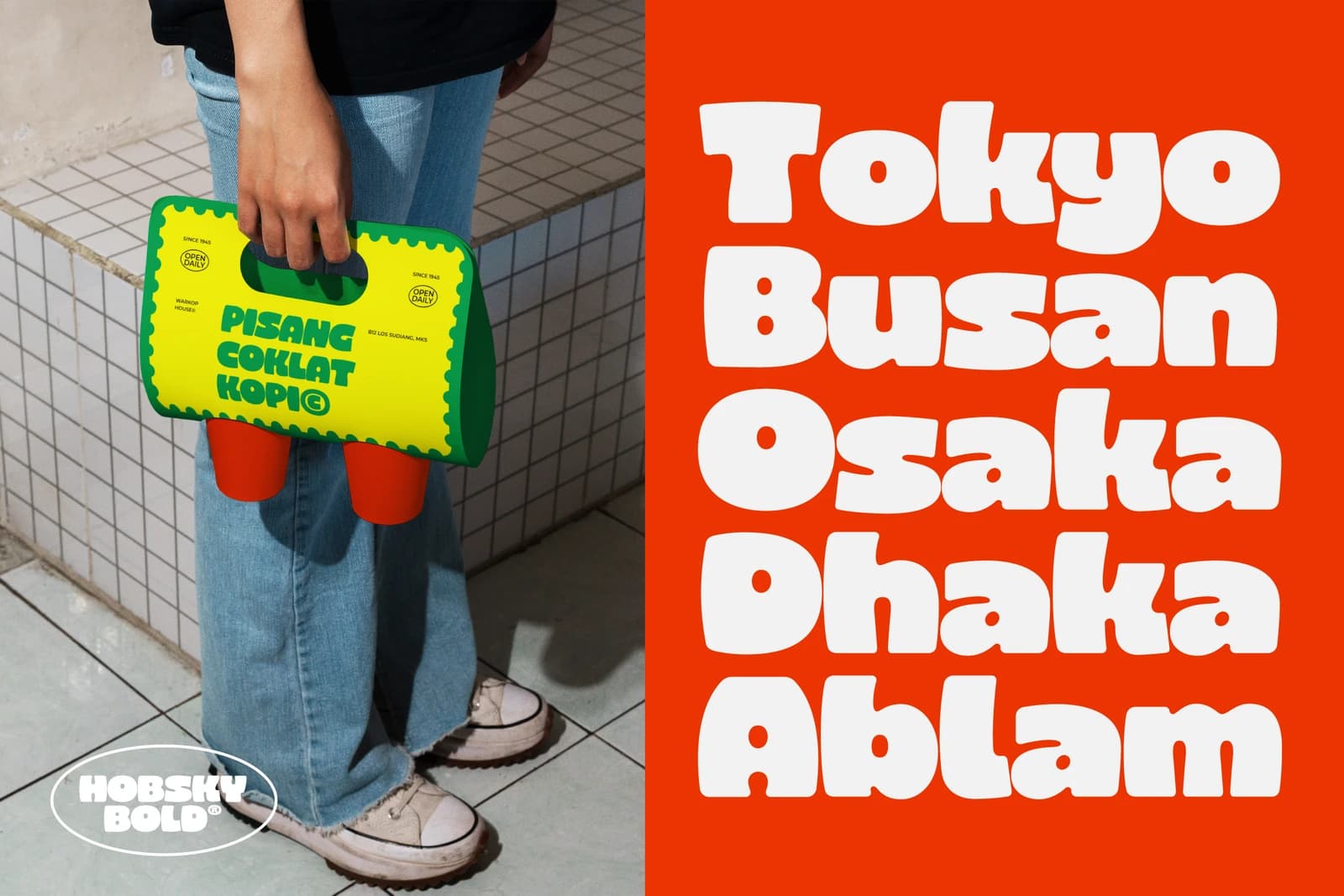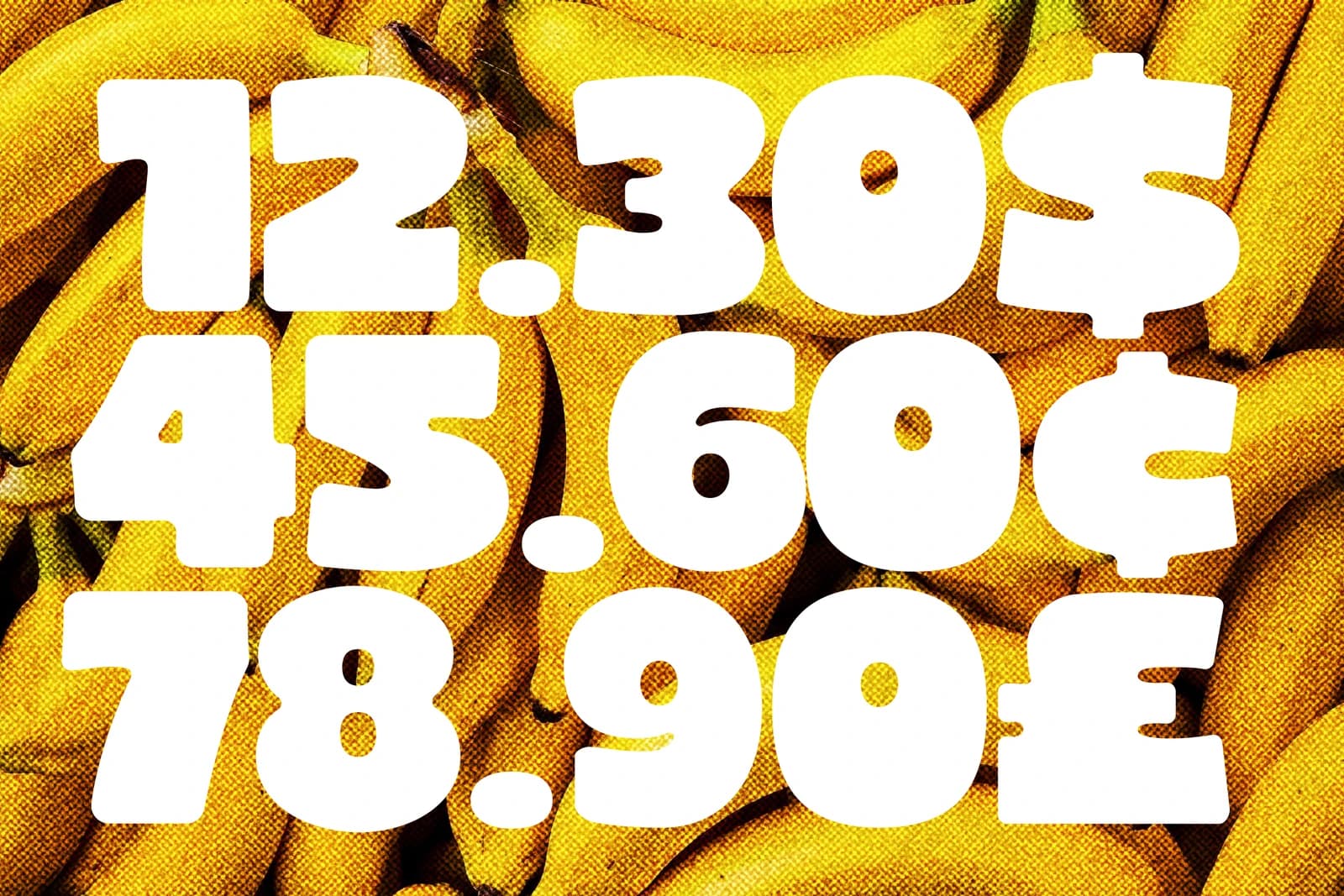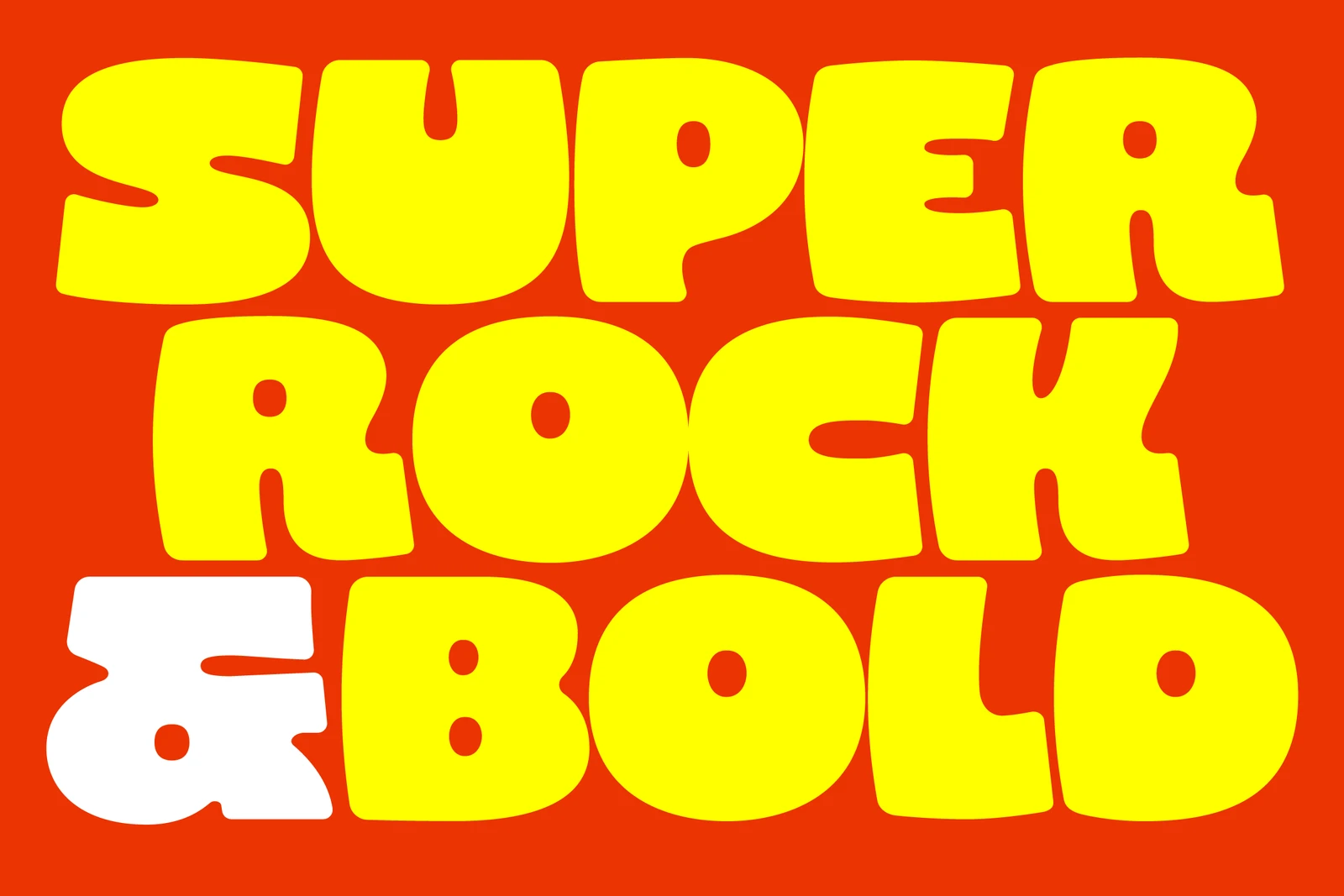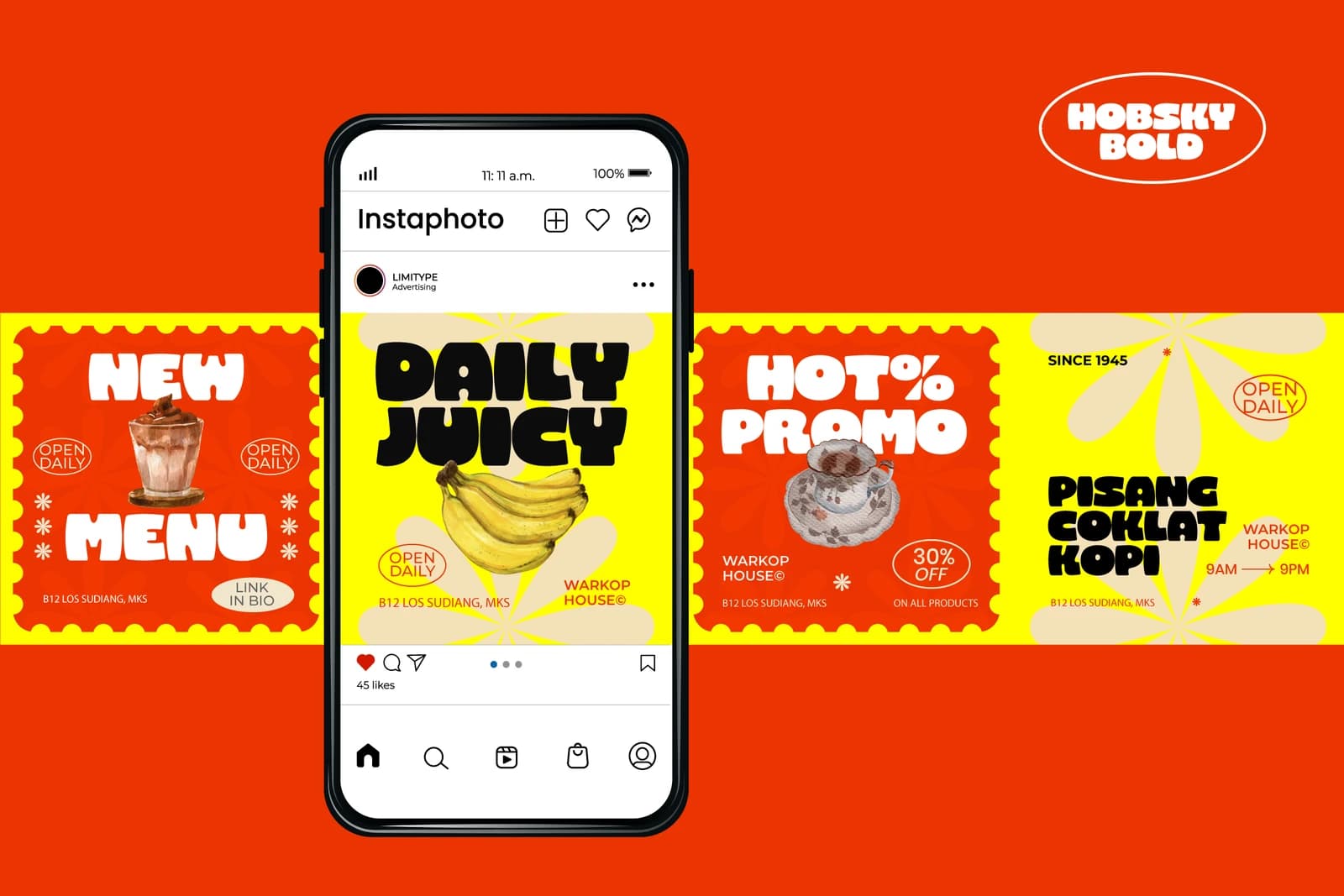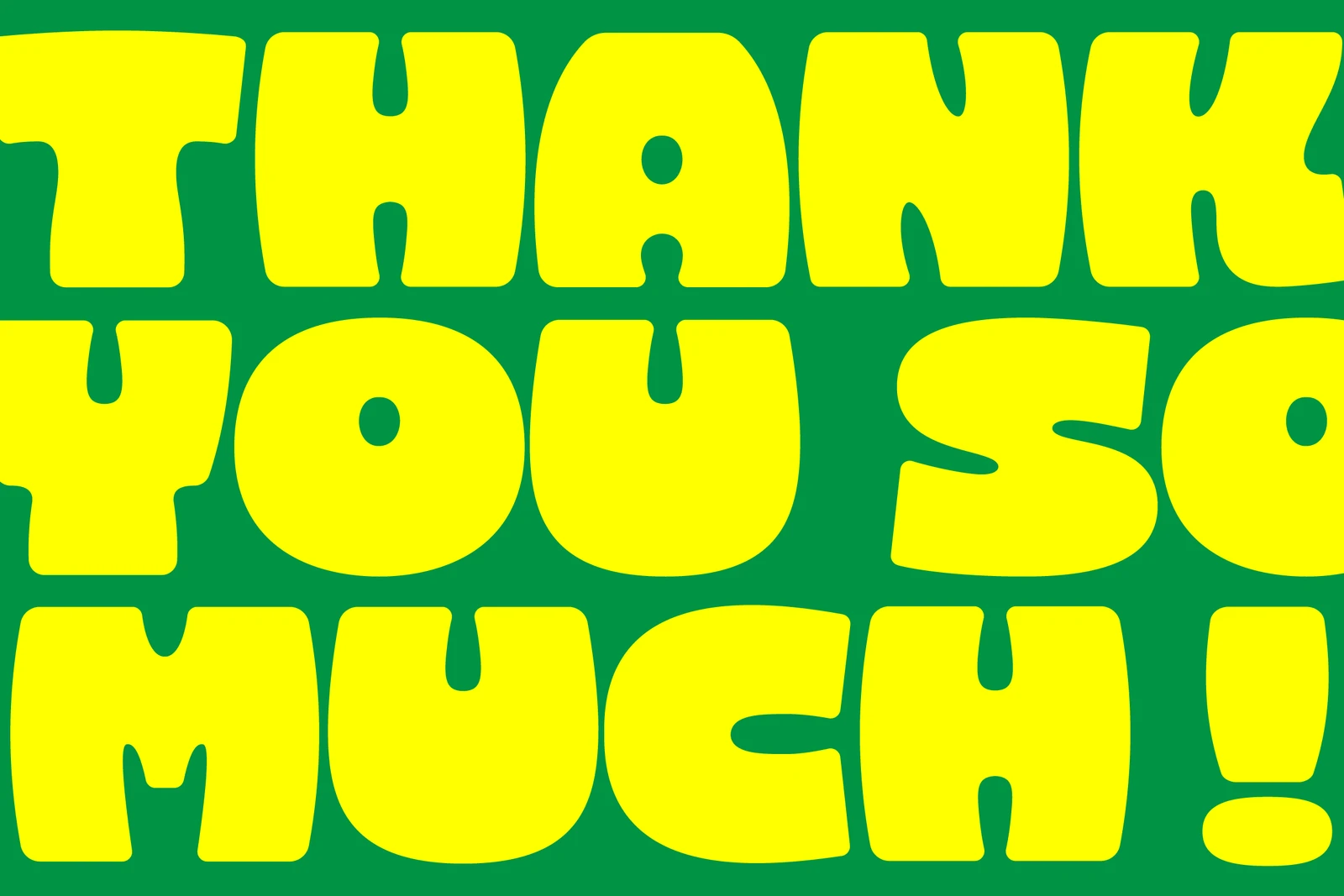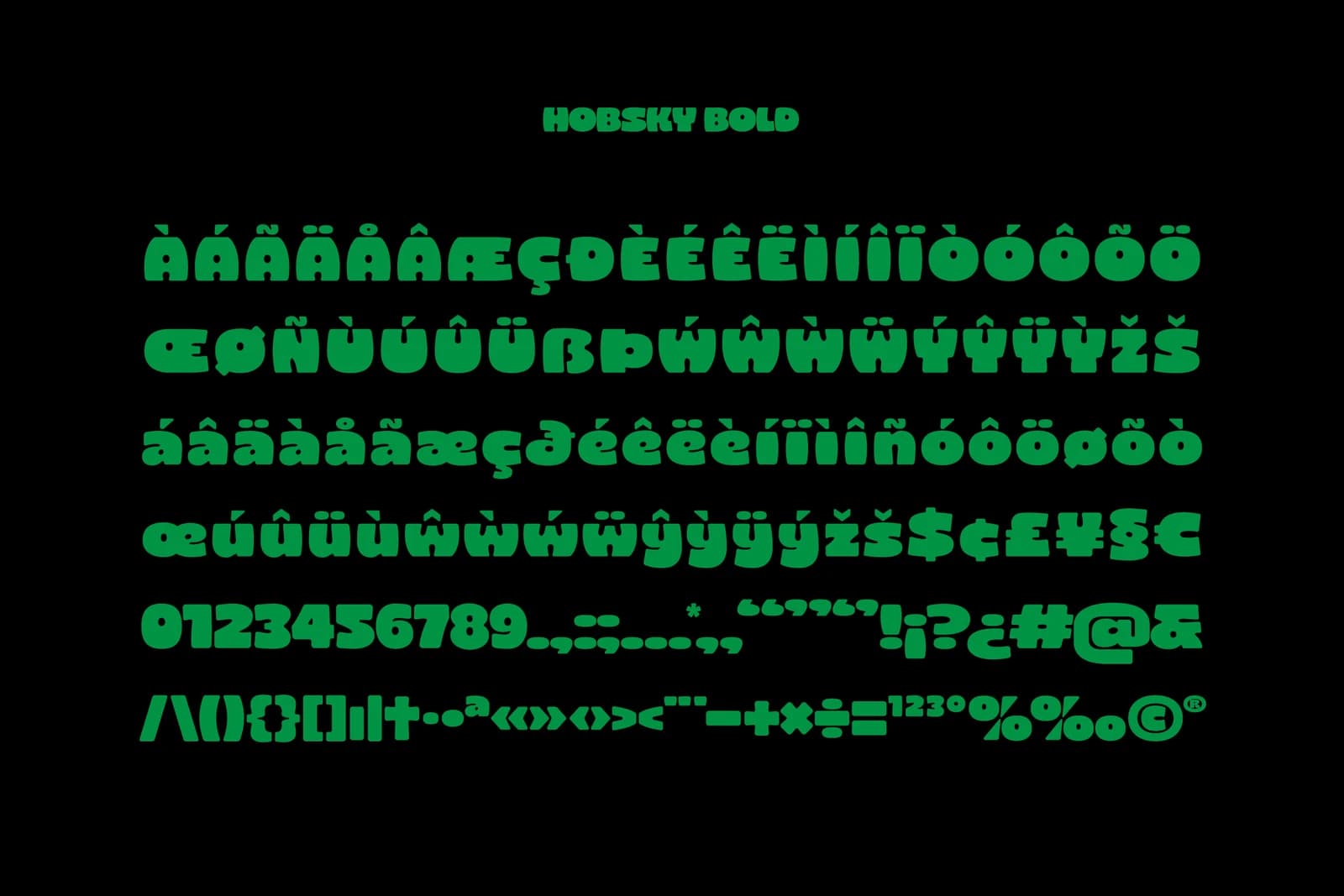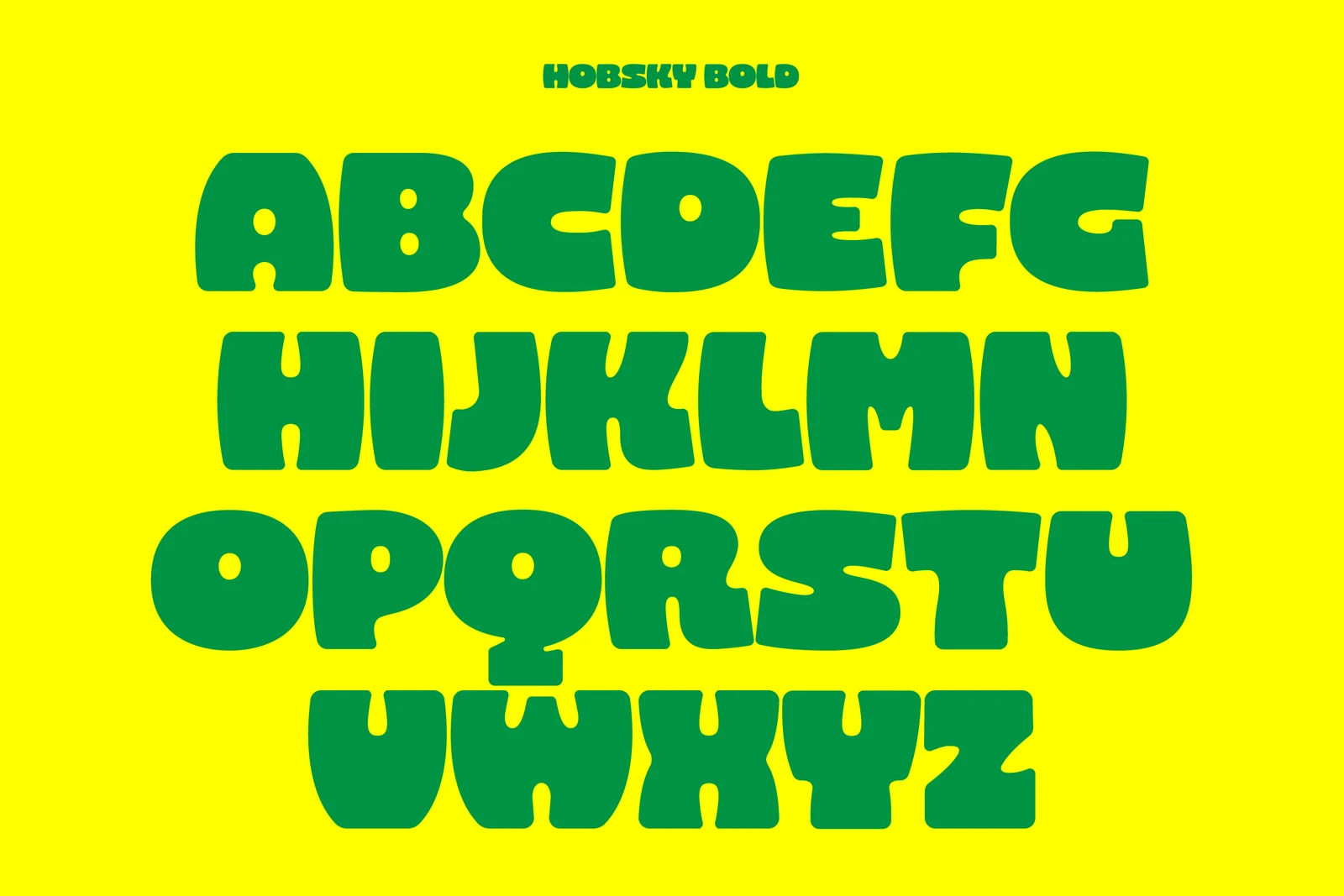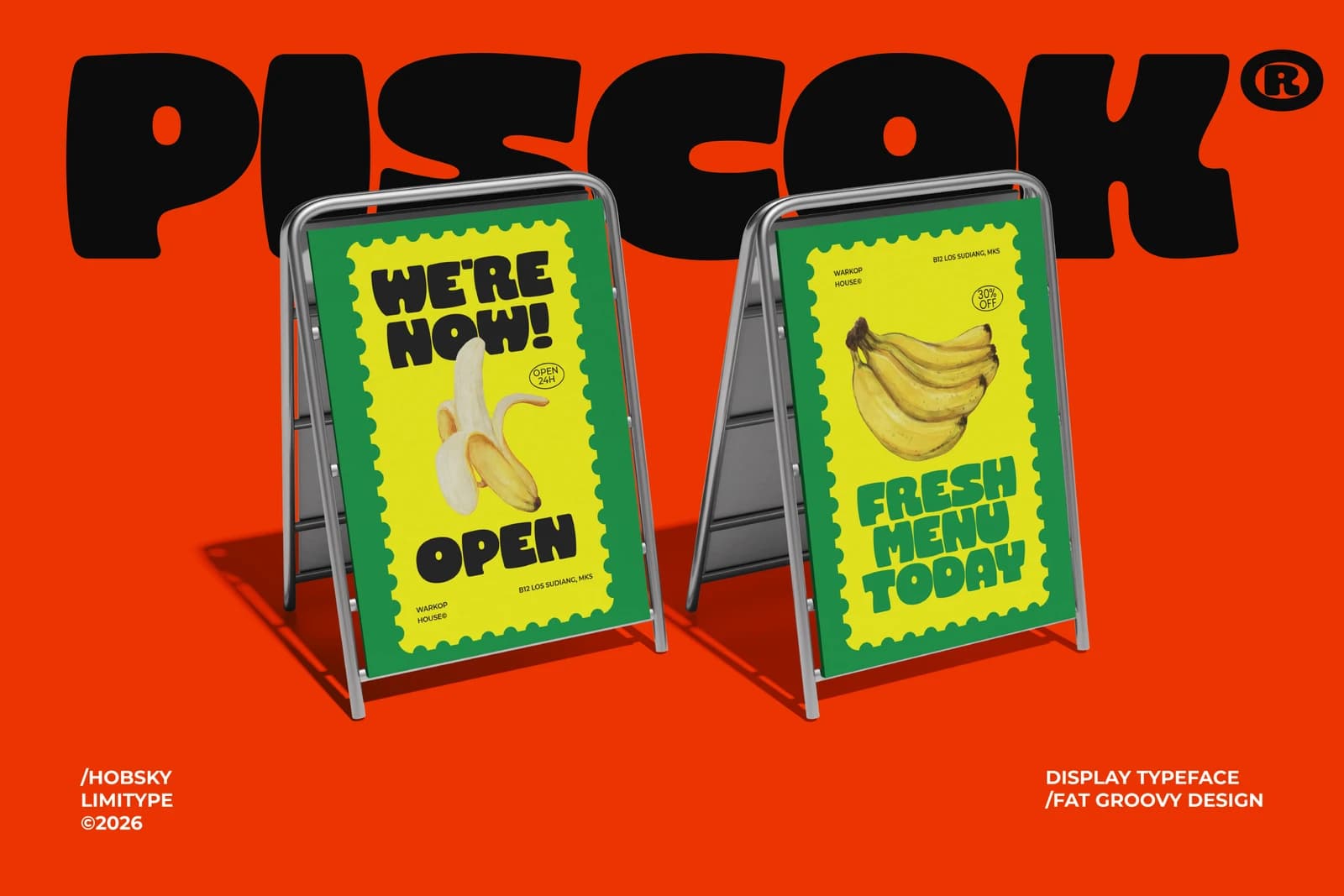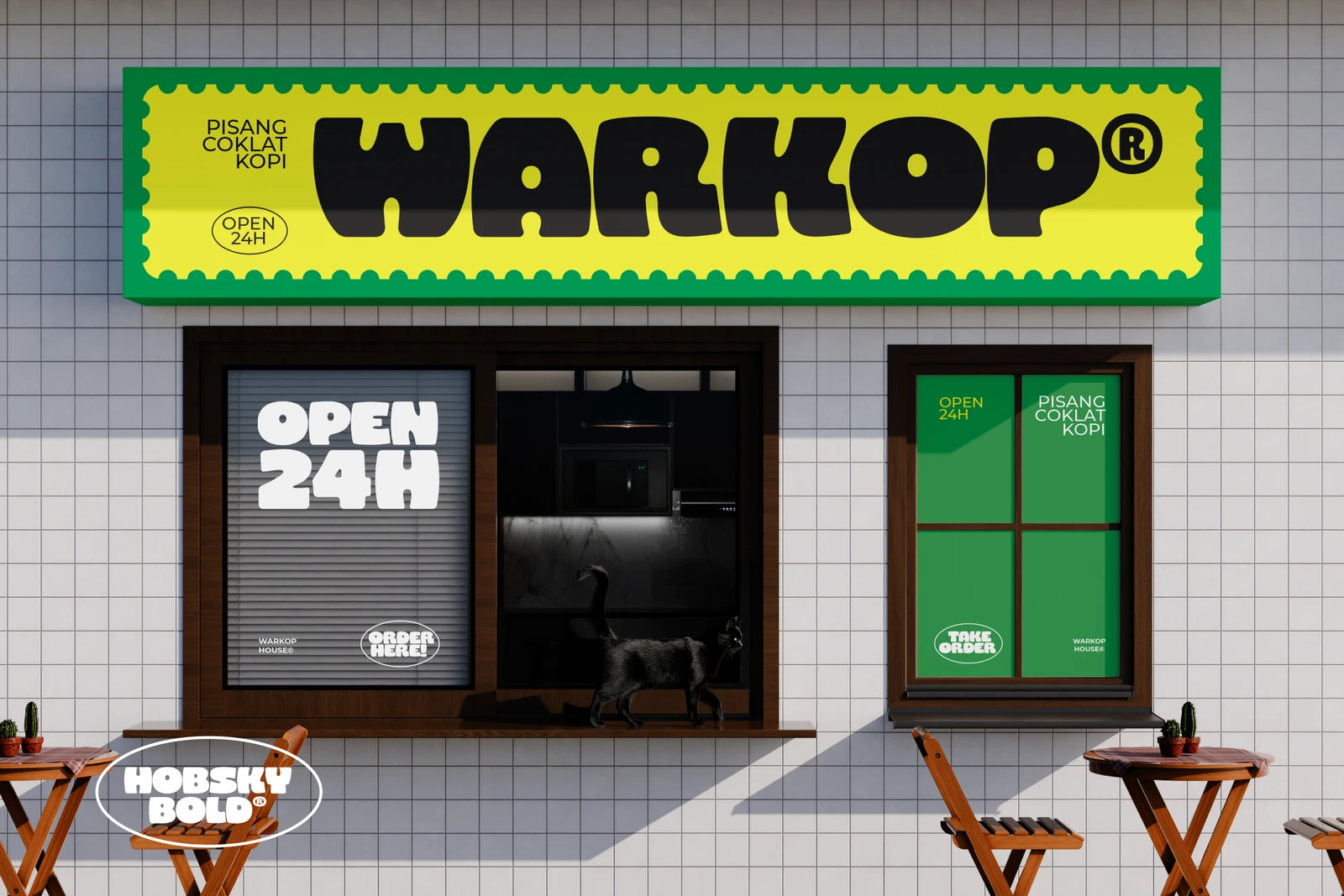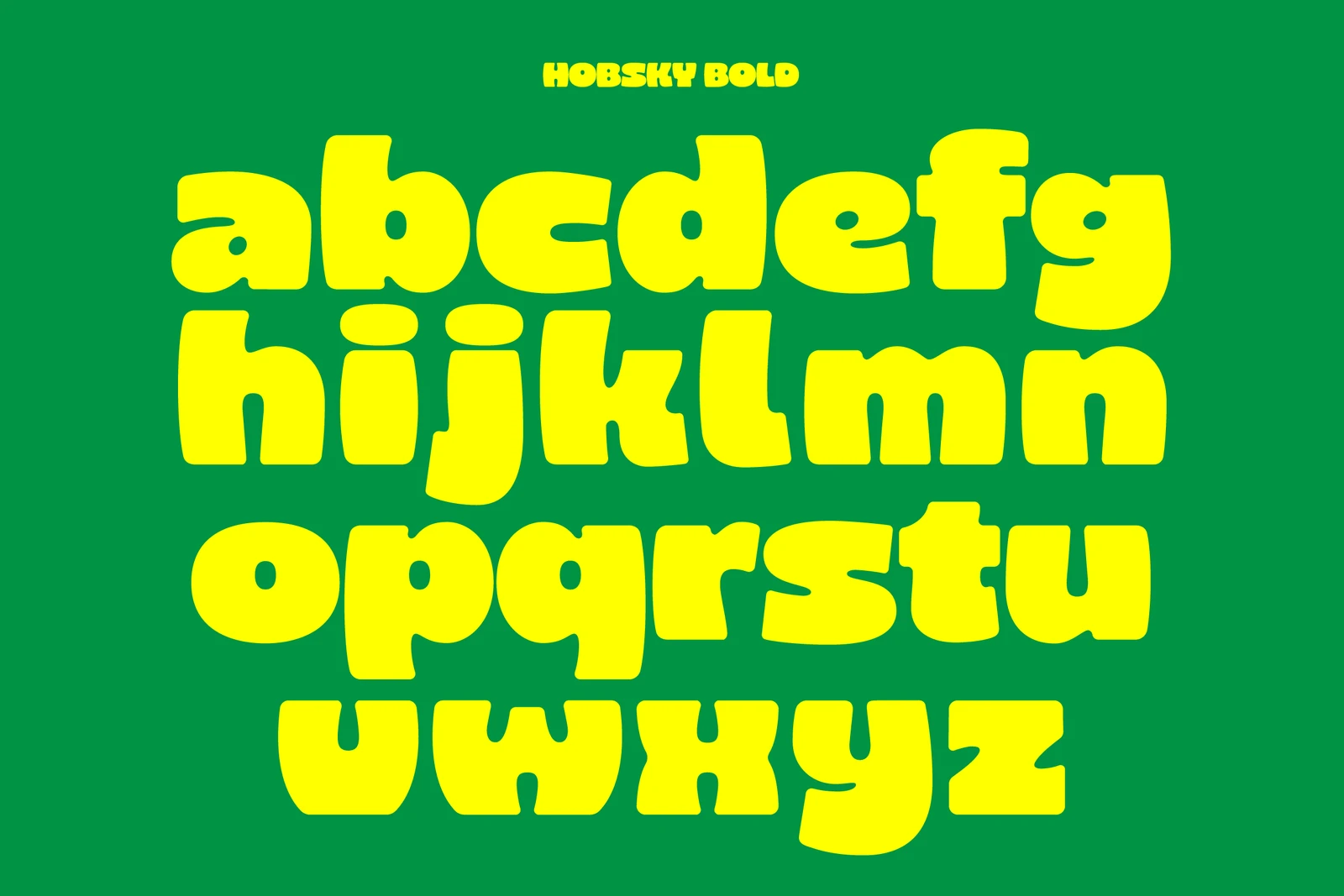
Hobsky - Bold Font
Hobsky, büyük kıvrımları, kalın vuruşları ve pürüzsüz geometrik yapısıyla dikkat çeken cesur bir ekran yazı tipidir. Yazı tipi, ilk bakışta güçlü bir grafik etki yaratır.
Karakterleri, retro esintili bir tavrı modern minimalizmle birleştirerek enerjik, şık ve son derece çok yönlü bir yazı tipi oluşturur. Hobsky, logolar, posterler, sokak giyimi ve yaratıcı kampanyalar için etkilidir; basit metni kişilik ve etkiyle güçlü bir görsel ifadeye dönüştürür.